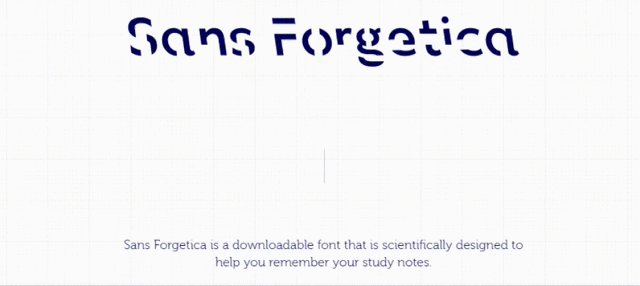
Nhằm giúp sinh viên ghi nhớ tốt hơn các bài giảng của mình, các nhà nghiên cứu tại Đại học Royal Melbourne Institute of Technology (RMIT), Úc đã phát triển một font chữ hoàn toàn mới có tên là Sans Forgetica.
Font chữ này là một typeface (nét chữ) dạng sans serif đặc biệt với nhiều nét đứt và nghiêng về bên trái, một thiết kế không thường được sử dụng trong việc in máy.
Các nét đứt này là chủ ý của các nhà nghiên cứu nhằm khiến Sans Forgetica trở nên khó đọc hơn. Bởi người đọc sẽ phải chú ý nhìn từng chữ lâu hơn, bộ não phải sử dụng khả năng "xử lý nhận thức sâu hơn" và điều này sẽ giúp lưu giữ ký ức tốt hơn.
400 sinh viên đã tham gia một thử nghiệm nhằm tìm ra font chữ tốt nhất giúp nâng cao trí nhớ. Kết quả cho cho thấy, sau khi được tiếp xúc một loạt font chữ khác nhau, Sans Forgetica đã đạt được kết quả tốt nhất.
Giải thích về khả năng ghi nhớ tốt nhất của Sans Forgetica, Chủ tịch của Phòng thí nghiệm Behavioural Business của RMIT, tiến sĩ Jo Peryman cho biết, các nét trong font chữ Sans Forgetica ngắt quãng vừa đủ nên nó không quá khó đọc.
Dù mục đích ban đầu của các nhà nghiên cứu khi tạo ra font chữ Sans Forgetica là nghiên cứu và học tập nhưng tiến sĩ Janneke Blijlevens, thành viên sáng lập của phòng thí nghiệm Behavioural Business tin rằng font chữ này và các ứng dụng của nó có thể mở rộng để giúp mọi người ghi nhớ được những thứ quan trọng trong cuộc sống.